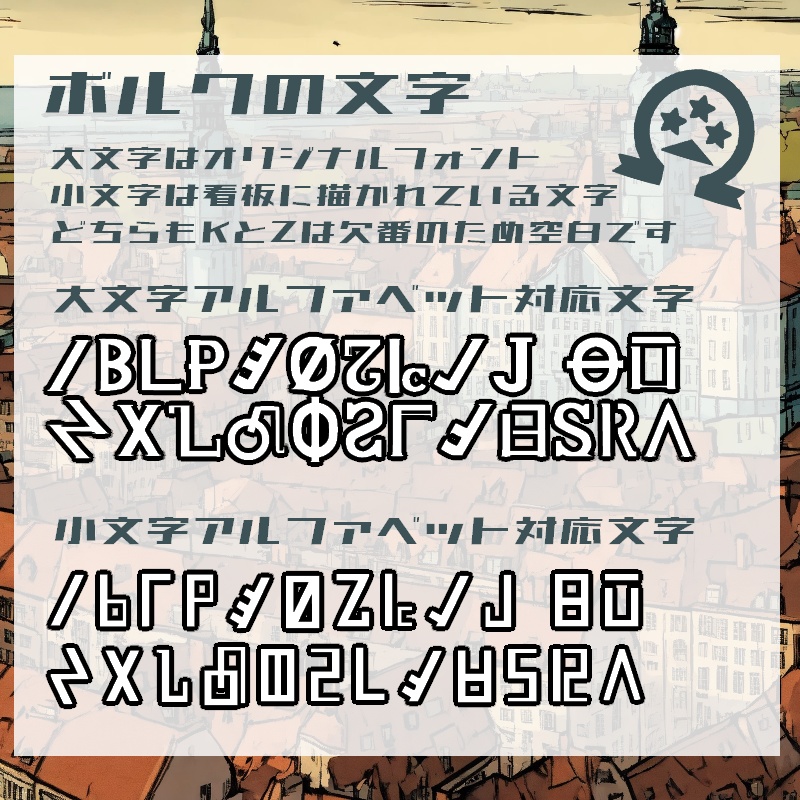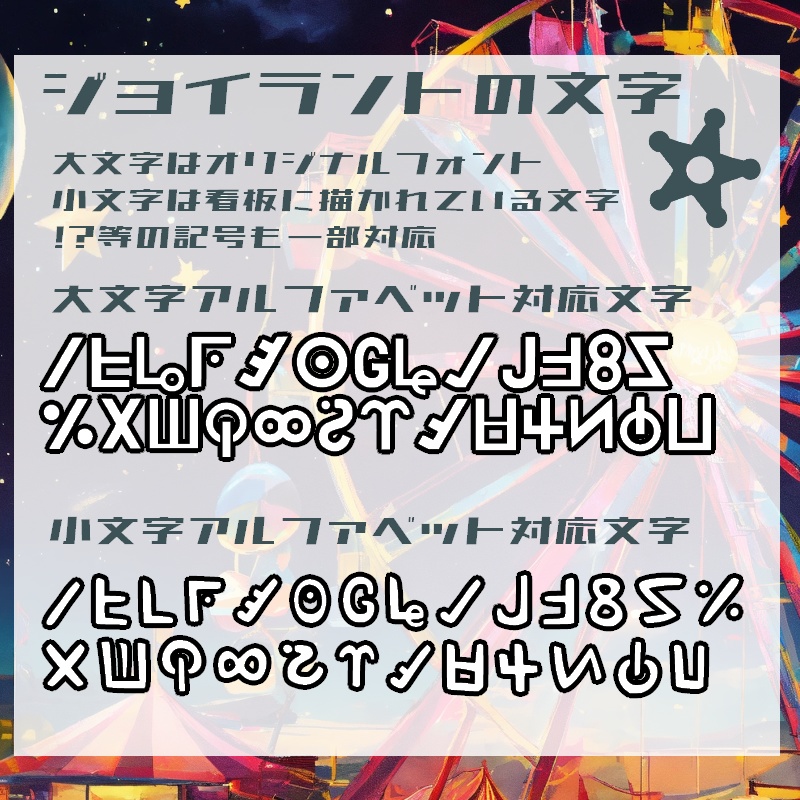
Lunatia Font
『Lunatia Font』はクロノア2 世界の望んだ忘れもの に登場する架空文字を可能な限り解読し設計したフォントです. クロノア作品での創作活動などにお役立ていただけると幸いです. このフォントファイルにはPS版風のクロノアおよび,Wiiリメイク版で使用された文字が含まれています. Volkのフォントには『K』および『Z』のフォントが存在しないことが明らかとなった為,該当のフォントは空欄となっています. Joylantのフォントを更新しました. 『F』『W』『!』『?』の正しいフォントが判明したため追加しました. 対応文字や細かい仕様については同封のreadmeテキストを参照してください. =========================================== このフォントはデザイン用途にご使用いただけます. 【利用規約】 ・印刷物,映像作品,グッズ作成等での利用はOK ・ロゴマーク等への画像への加工使用もOK ・スクリーンショット/撮影/公開はOK ・改変/再配布/自作発言はNGです 利用報告は必須ではありませんが,報告してくれると作者が喜びます.